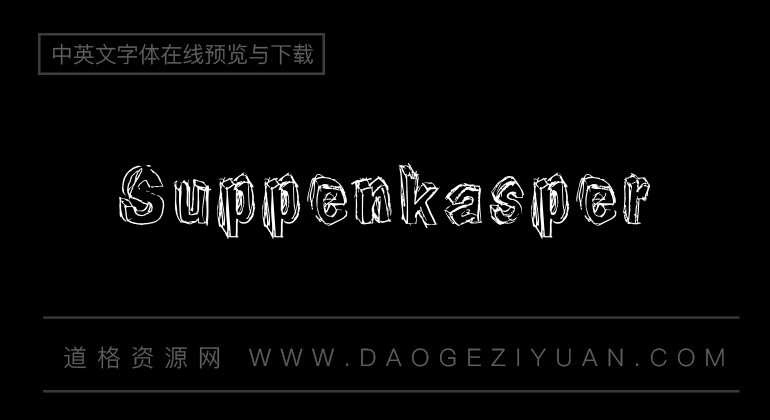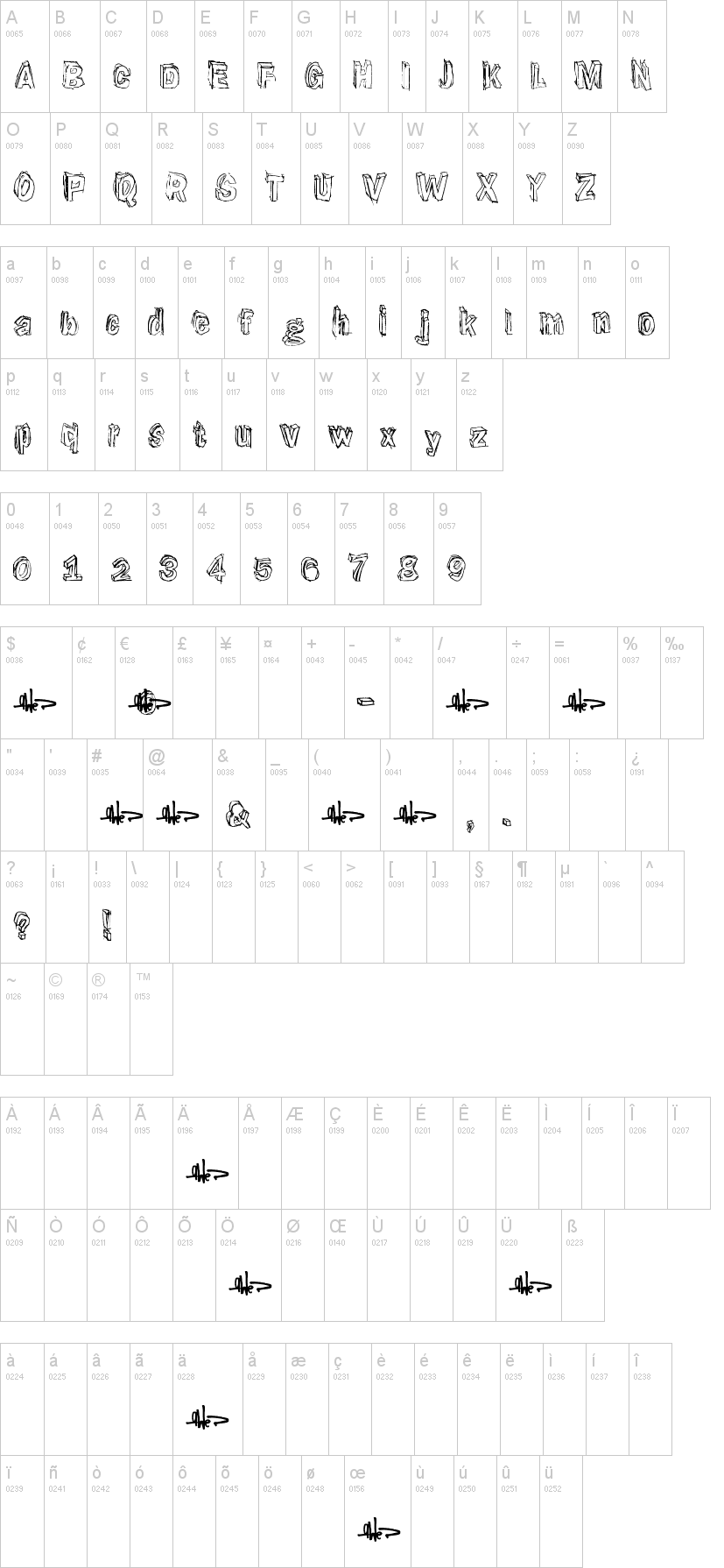
Suppenkasper
Suppenkasper是一款由德国设计师Gert Wunderlich设计的新字体。它具有细节丰富的形状,而且拥有独特的风格,可以在视觉上为文本提供很好的表现力。它拥有一种温暖的感觉,可以让文字看起来更有趣,更有趣。它也有一些比较独特的特点,比如它的字母形状是圆润的,可以更好地表达文字的含义。
Suppenkasper是一款非常不错的手写艺术字体,具有很好的视觉感,适合于文化类的宣传设计、商业类品牌的广告和产品包装设计以及个性化文字排版等较多场景。
Suppenkasper字符映射图